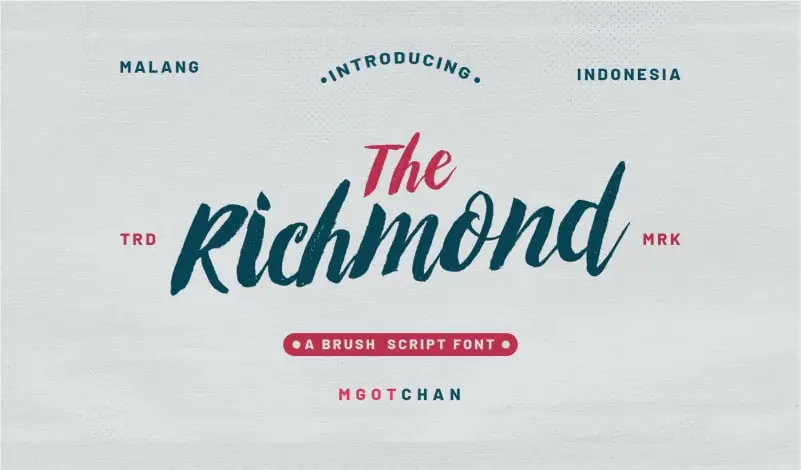
Richmond Brush Font
A Richmond Brush Font é uma elegante seleção para aqueles que buscam adicionar um toque de personalidade às suas criações digitais. Este script brush font foi criado pelo designer MGOT CHAN, exibindo um estilo natural e robusto. Com base simples e um traço robusto, a Richmond Brush Font é perfeita para aplicações como marca, design de etiquetas, tipografia de logotipo, frases, posters e muito mais. Para obter melhores resultados, o designer recomenda combinar esta font com outras tipografias serif/sans-serif para adicionar profundidade ou um toque mais leve. Aconselha-se evitar o uso da variação regular, que pode não se adequar tão bem ao estilo de Richmond Brush Font. Este é um recurso ideal para designs em títulos como roupas, convites, livros de título, materiais de estação, frases, marcas, logotipos, cartões de cumprimentos, camisas, embalagens e posters. Com sua simplicidade e robustez únicas, a Richmond Brush Font pode se adaptar perfeitamente aos mais variados usos, tornando-a uma opção valiosa para qualquer designer gráfico atento às últimas tendências.